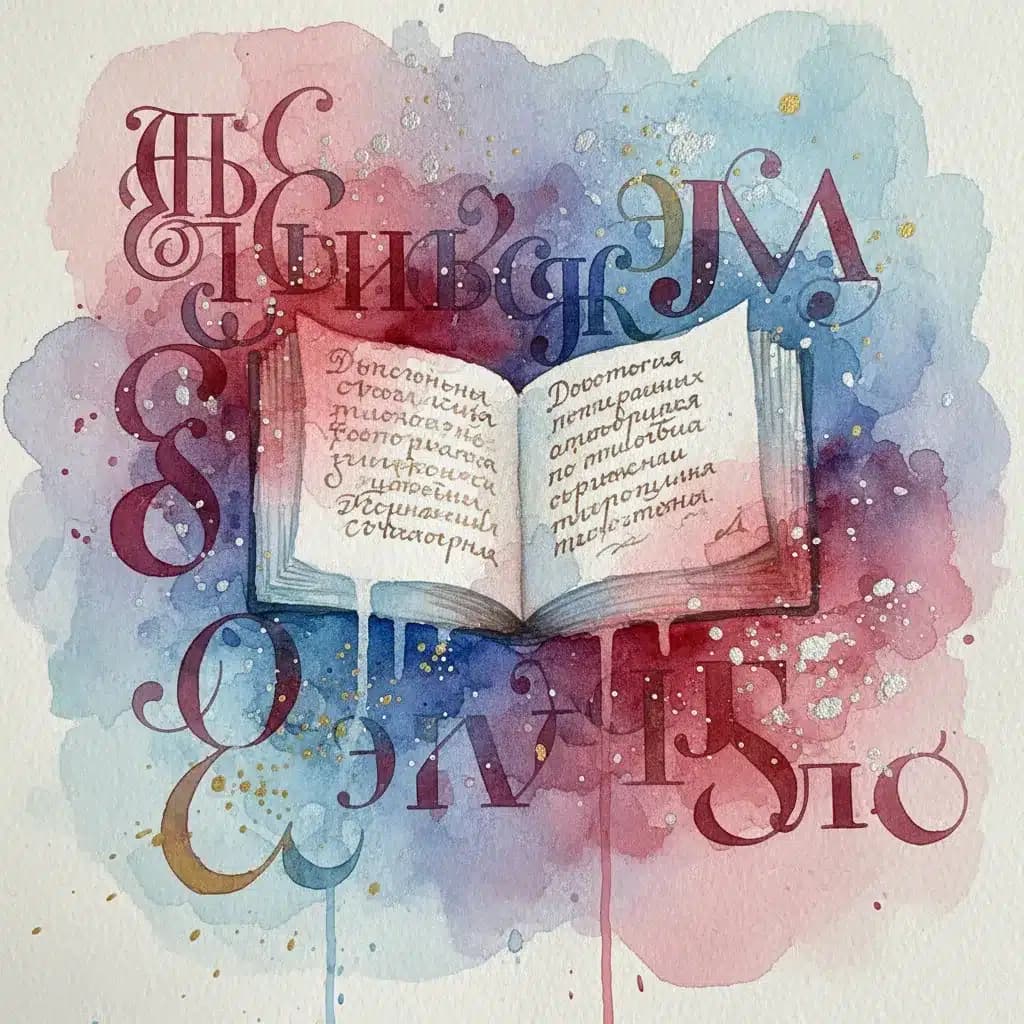
אם אי פעם ניסיתם לעצב חומר שיווקי, אתר אינטרנט או מצגת בשפה הרוסית וגיליתם שהפונט שבחרתם פשוט לא נראה טוב – אתם לא לבד. בחירת פונטים לטקסט קירילי היא אתגר ייחודי שדורש הבנה מעמיקה של המבנה הייחודי של האותיות הרוסיות, הקריאות והאסתטיקה התרבותית. הבעיה היא שרוב המעצבים מתמקדים באותיות לטיניות ועבריות, ושוכחים שהאלפבית הקירילי דורש התייחסות שונה לחלוטין – מבחינת הפרופורציות, הצורות והקריאות.
למה זה באמת משנה? כי פונט לא מתאים בטקסט רוסי יכול להרוס את כל העיצוב – גם אם הוא נראה מושלם באנגלית או עברית. האותיות הקיריליות (כמו Ж, Ф, Щ, Ы) מורכבות יותר מאותיות לטיניות, עם יותר קווים ופרטים. פונט שלא תוכנן במיוחד לרוסית עלול להציג אותן בצורה לא מאוזנת, קשה לקריאה או פשוט לא מקצועית.
במדריך הזה תלמדו את הקריטריונים המקצועיים לבחירת פונטים ברוסית, תכירו את הסוגים השונים ותקבלו כלים מעשיים לבחירה נכונה – בין אם אתם מעצבים אתר בינלאומי, יוצרים חומרי שיווק לשוק הרוסי או פשוט רוצים שהעיצוב שלכם יראה מקצועי.
האלפבית הקירילי הוא מערכת כתיבה ייחודית עם 33 אותיות ברוסית, שחלקן דומות לאותיות לטיניות אבל רבות אחרות שונות לחלוטין. ההבדל המרכזי הוא שאותיות קיריליות נוטות להיות רחבות יותר ומורכבות יותר מבחינה ויזואלית – עם יותר קווים, עיגולים ופרטים עדינים שצריכים להישמר גם בגדלים קטנים.
הנה השוני המרכזי בין שלושת סוגי האלפבית:
במחקרי טיפוגרפיה קירילית נמצא שקריאות טקסט רוסי יורדת בכ-15-20% כאשר משתמשים בפונט שלא תוכנן במיוחד לאלפבית הזה – בהשוואה לפונטים מותאמים. זה נובע מהעובדה שהעין הרוסית מזהה דפוסים ספציפיים של אותיות, וכאשר הפרופורציות שלהן משתנות, המוח צריך לעבוד קשה יותר לפענח את הטקסט.
נקודת מפתח:פונט שנראה מצוין באנגלית או עברית עשוי להיות בעייתי לטקסט רוסי. תמיד בדקו את הפונט עם טקסט רוסי אמיתי (לא רק עם מספר אותיות בודדות) כדי לוודא שהוא קריא ומאוזן.
כמו בכל שפה, גם בטיפוגרפיה רוסית יש מספר קטגוריות עיקריות של פונטים, כאשר כל אחת מתאימה לשימושים שונים. הבחירה בין הקטגוריות תלויה בהקשר – האם מדובר בטקסט ארוך, כותרות, חומר מודפס או תצוגה דיגיטלית.
פונטים סריף מאופיינים בקווים קטנים (סריפים) בקצוות האותיות. בטיפוגרפיה רוסית, הסריפים עוזרים להדגיש את המבנה המורכב של האותיות ולשפר את הקריאות בטקסט ארוך – במיוחד בחומר מודפס. פונטים כמו Times New Roman Cyrillic או PT Serif הם דוגמאות קלאסיות.
מתי להשתמש: ספרים, מגזינים, מאמרים אקדמיים, מסמכים רשמיים, חומר מודפס שדורש קריאות גבוהה לאורך זמן. הסריפים מנחים את העין לאורך השורה ומפחיתים עייפות בקריאה ממושכת.
פונטים סנס-סריף הם פונטים ללא קווים בקצוות האותיות, עם קווי מתאר נקיים ומינימליסטיים. הם המועדפים לעיצוב דיגיטלי מודרני בגלל הקריאות המצוינת שלהם על מסכים ברזולוציות שונות. דוגמאות פופולריות כוללות את Roboto, Open Sans ו-PT Sans.
מתי להשתמש: אתרי אינטרנט, אפליקציות מובייל, ממשקי משתמש, פרסומות דיגיטליות, כותרות ותפריטים. הפשטות של פונטים אלה הופכת אותם לאידיאליים לתצוגה על מסכים בכל הגדלים – מטלפונים ניידים ועד מסכי מחשב גדולים.
פונטים סקריפט מחקים כתב יד זורם, בעוד שפונטים קליגרפיים מדגישים אלמנטים אומנותיים ומעוטרים. בטיפוגרפיה רוסית, קטגוריה זו כוללת גם פונטים בהשראת כתבים היסטוריים רוסיים – כמו כתב כנסייתי סלאבי עתיק.
מתי להשתמש: הזמנות לחתונות, לוגואים, כרזות אומנותיות, עטיפות ספרים ופרויקטים שדורשים אופי ייחודי ומיוחד. חשוב להשתמש בהם במשורה – רק לכותרות קצרות או למבטאים ויזואליים, לא לטקסט ארוך שצריך להיות קריא.
טיפ מקצועי:אל תשתמשו בפונט סקריפט או קליגרפי לטקסט שלם. הם מתאימים רק לכותרות, לוגואים או הדגשות קצרות. לטקסט גוף, תמיד בחרו סריף או סנס-סריף קריא.
מעבר לסגנון הוויזואלי, יש קריטריונים טכניים חשובים שצריך לבדוק לפני שבוחרים פונט לפרויקט ברוסית. אלה הם הגורמים שקובעים האם הפונט יעבוד טוב בפועל – ולא רק יראה יפה בתמונת דוגמה.
לא כל פונט שטוען שהוא "תומך ברוסית" באמת כולל את כל התווים הנדרשים. האלפבית הרוסי כולל 33 אותיות בסיסיות, אבל פונט מקצועי צריך לכלול גם:
איך לבדוק: הדביקו טקסט רוסי מלא (כולל כל האותיות) לתוך תוכנת העיצוב או דפדפן האינטרנט ובדקו שאין תווים חסרים או מוחלפים בריבועים/סימני שאלה. משפט מומלץ לבדיקה: "Съешь ещё этих мягких французских булок, да выпей чаю" (משפט שמכיל את כל האותיות הרוסיות).
פונט טוב לרוסית צריך להישאר קריא בכל טווח הגדלים שבו תשתמשו – מ-10-12 פיקסלים (טקסט הערות שוליים) ועד 48+ פיקסלים (כותרות גדולות). אותיות קיריליות מורכבות כמו Ж, Ф ו-Щ צריכות לשמור על הפרופורציות והפרטים שלהן גם כשהן מוקטנות.
מחקרים בתחום טיפוגרפיה דיגיטלית מראים שפונטים עם x-height גבוה יותר (גובה האותיות הקטנות ביחס לגובה הכולל) נוטים להיות קריאים יותר במסכים – במיוחד ברזולוציות נמוכות או על מכשירים ניידים. לפי עקרונות הטיפוגרפיה המקצועיים, יחס אופטימלי הוא כאשר x-height תופס 50-55% מגובה האות הגדולה.
פרויקט עיצובי מקצועי דורש היררכיה טיפוגרפית – כותרות, כותרות משנה, טקסט גוף, הדגשות ועוד. לכן חשוב לבחור משפחת פונטים שכוללת מספר משקלים (Light, Regular, Medium, Bold, Black) וסגנונות (רגיל, נטוי/איטליק).
לדוגמה, למשפחת פונטים איכותית יש לפחות 4-6 משקלים שונים. זה מאפשר לכם ליצור ניגודיות ברורה בין רמות המידע השונות מבלי לערבב פונטים שונים – מה ששומר על עקביות ויזואלית.
עכשיו כשאתם מכירים את הקריטריונים, הנה תהליך שלב אחר שלב לבחירת הפונט המושלם לפרויקט הרוסי שלכם:
שלב 1: הגדירו את הקונטקסט והשימוש
לפני שמתחילים לחפש, ענו על השאלות הבאות: האם הפונט מיועד למסך או להדפסה? האם יהיה טקסט ארוך או רק כותרות קצרות? מהו קהל היעד (צעיר/מבוגר, פורמלי/קז'ואל)? מה האופי הרצוי של המותג (מודרני/קלאסי, רציני/משחקי)?
בעולם הדיגיטלי של היום, טיפוגרפיה איכותית היא לא רק עניין אסתטי – היא משפיעה ישירות על חוויית המשתמש, הקריאות וההמרות. השקעה קטנה של זמן בבחירת הפונט הנכון יכולה לעשות הבדל עצום בהצלחת הפרויקט שלכם – בין אם זה אתר מסחרי, חומרי שיווק או מוצר דיגיטלי.